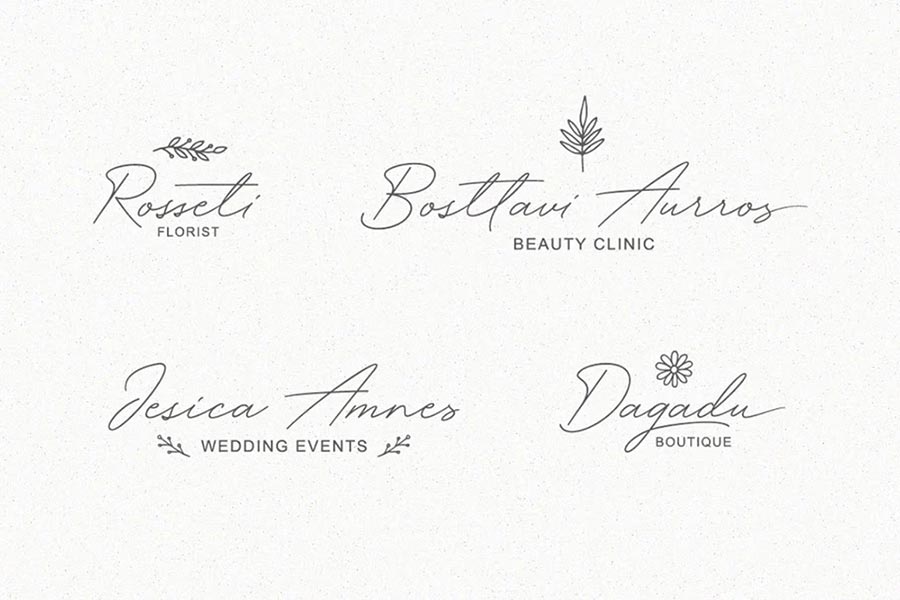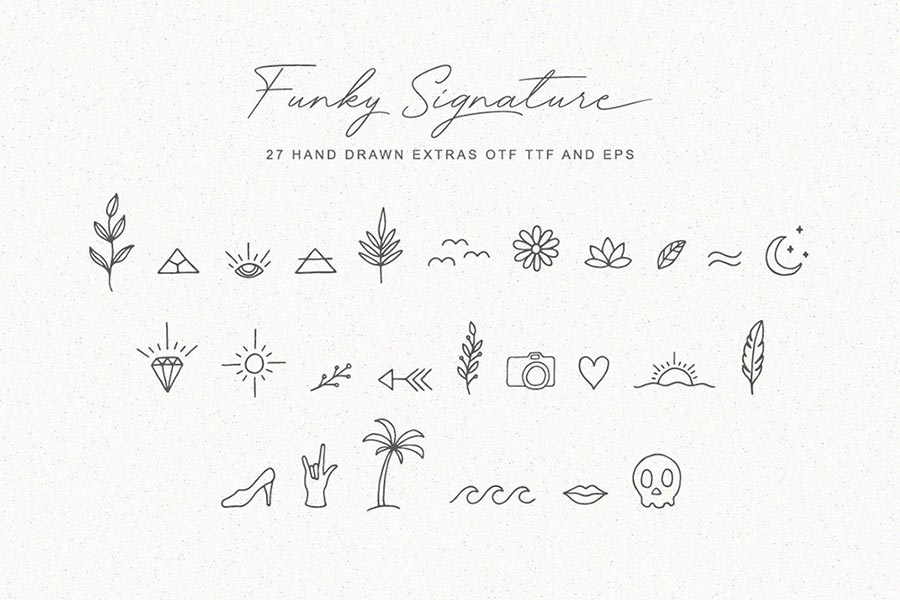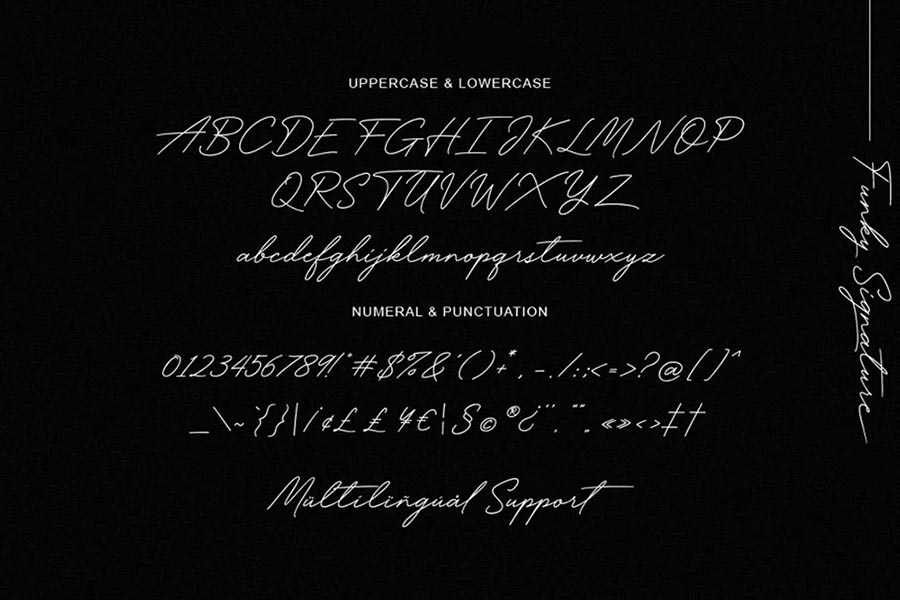
Chia Sẻ Miễn Phí Font Việt Hóa - Signature Chữ Viết Tay Nét Đẹp Tự Nhiên Và Cổ Điển
Sadesign.vn chia sẻ miễn phí font chữ Việt hóa Signature, mang phong cách chữ viết tay đầy tự nhiên và cổ điển. Đây là một lựa chọn tuyệt vời cho các designer đang tìm kiếm một font chữ tinh tế, dễ sử dụng và có thể tạo điểm nhấn đặc biệt cho các dự án thiết kế. Dù bạn làm việc với các dự án thiết kế logo, thiệp mời hay các sản phẩm sáng tạo khác, font Signature sẽ giúp mang lại vẻ đẹp thanh thoát và sang trọng cho các sản phẩm của bạn.
Sự Đặc Biệt Của Font Chữ Signature
Font chữ Signature mang đến cho các designer một phong cách viết tay tự nhiên, nhẹ nhàng nhưng đầy ấn tượng. Những đường cong mềm mại, thanh thoát của từng chữ cái trong font này khiến chúng ta liên tưởng đến nét chữ viết tay của những người nghệ sĩ tài ba. Với khả năng kết hợp giữa sự cổ điển và hiện đại, font chữ này rất phù hợp cho các thiết kế yêu cầu tính thẩm mỹ cao, từ các sản phẩm thiết kế thương hiệu đến các thiệp mời, bao bì hoặc logo.
Lý Do Nên Chọn Font Signature Cho Các Dự Án Thiết Kế
1. Phong Cách Độc Đáo Và Ấn Tượng
Font Signature mang lại một phong cách độc đáo và khác biệt so với những font chữ thông thường. Nhờ vào vẻ đẹp tự nhiên, nhẹ nhàng, kiểu chữ này không chỉ thu hút người nhìn mà còn tạo ra sự lôi cuốn, ấn tượng lâu dài.
2. Tính Dễ Dàng Sử Dụng Và Tùy Biến Cao
Bạn có thể áp dụng font này vào bất kỳ dự án thiết kế nào, từ các tài liệu in ấn cho đến các thiết kế online. Hơn nữa, với khả năng tùy chỉnh cao, font Signature dễ dàng thích ứng với mọi yêu cầu và phong cách thiết kế của bạn.
3. Hỗ Trợ Tốt Cho Tiếng Việt
Font chữ Signature không chỉ hỗ trợ tiếng Anh mà còn có đầy đủ các ký tự đặc biệt trong tiếng Việt. Điều này giúp các designer có thể sử dụng font này trong mọi dự án thiết kế có chứa tiếng Việt mà không lo gặp phải vấn đề về việc thiếu dấu hoặc không hiển thị đúng font. Với tính năng này, Signature trở thành lựa chọn lý tưởng cho các dự án thiết kế tại Việt Nam.
Font chữ Signature miễn phí từ Sadesign.vn là một công cụ tuyệt vời cho các designer muốn tạo ra những sản phẩm thiết kế độc đáo, sang trọng và có nét đẹp tự nhiên. Với tính năng Việt hóa đầy đủ, font chữ này không chỉ hỗ trợ tiếng Việt mà còn rất dễ sử dụng và tùy chỉnh. Hãy tải font Signature ngay hôm nay và bắt đầu tạo ra những thiết kế đẹp mắt và ấn tượng cho các dự án của bạn.